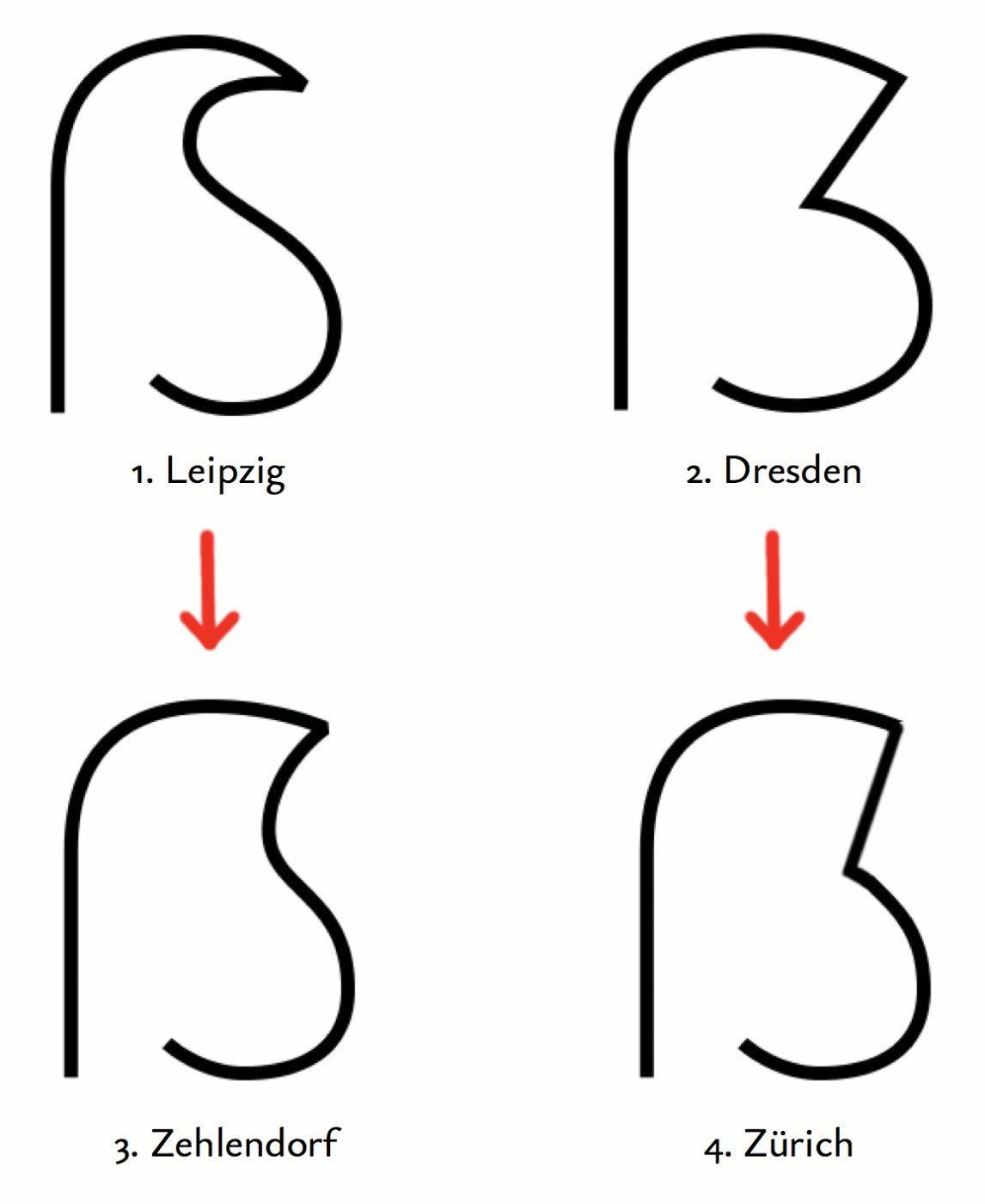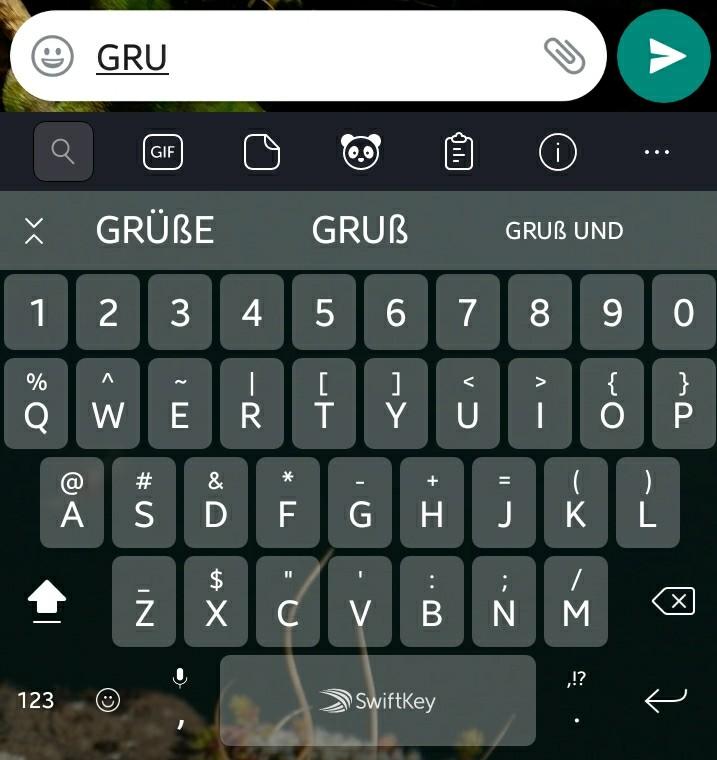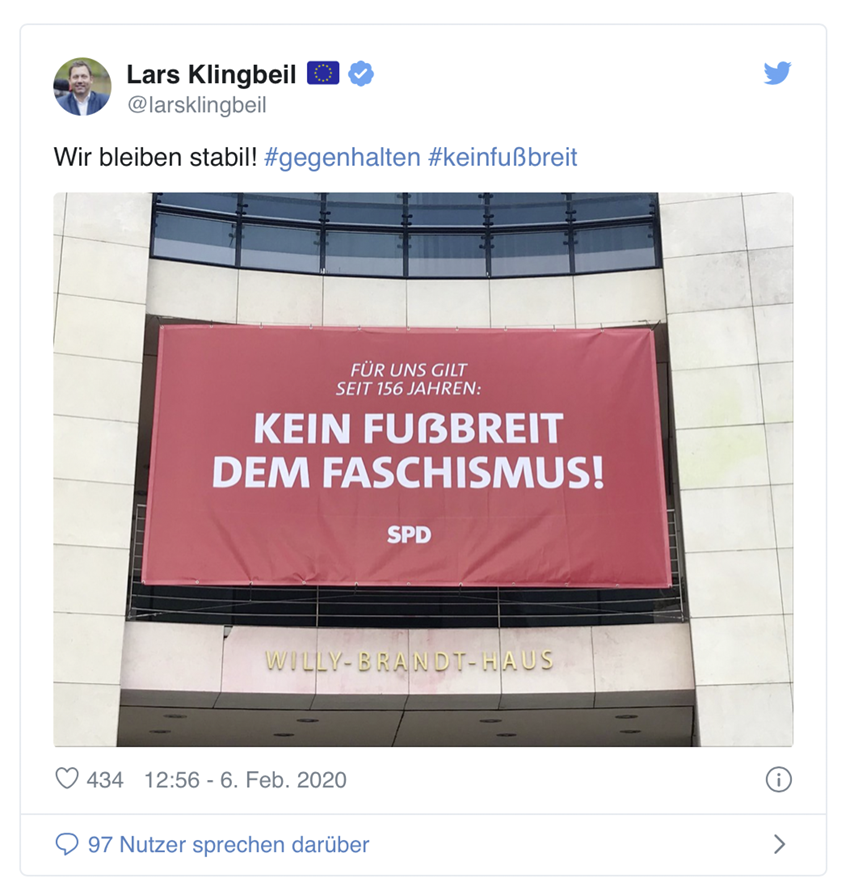
Ich empfinde die unterste bzw. rechte Version allerdings schon als zu breit, ebenso bei der Quinoa – aber das ist wahrscheinlich Geschmacksache. :-?
Ja, da gehen die Meinungen erfahrungsgemäß ziemlich auseinander. Ich vertret hier in erster Linie mal meine Meinung...
Jetzt wäre es eben nur interessant, wie man die Spielarten sonst benennen könnte, falls man sie gruppieren/klassifizieren möchte, wenn nicht nach den bereits gebräuchlichen Städtenamen. Jemand Vorschläge? :-?
Hatte nicht Andreas Stötzner in einem Paper ein modulares Klassifikationsschema vorgeschlagen? Ich finds grad nicht.
Städtenamen sind auf die Dauer sicher nicht praktisch. Ich kann mir selber nicht merken, welche was bedeuten...
Könnte nicht mal jemand visualisieren, wie sich Berliner, Dresdner, Frankfurter, Leipziger, Münchener, Weimarer (?) und Zehlendorfer Form (hab ich was vergessen?) unterscheiden. Dann hätte man immer eine bildliche Erinnerungsstütze zur Hand.
Ich bin ein Zürcher in Zürich und benutze ß und ẞ schamlos und überall. 🤓
Bin allerdings auch schon mal von einer Kollegin darauf hingewiesen worden, dass sich da ein ß in mein Physik-Skript «eingeschlichen» habe... 🙄  Und bei neuen Klassen sag ich auch immer was dazu, wenn ich an der Tafel zum ersten mal ein ß krakle (gibt immer etwas Gemurmel).